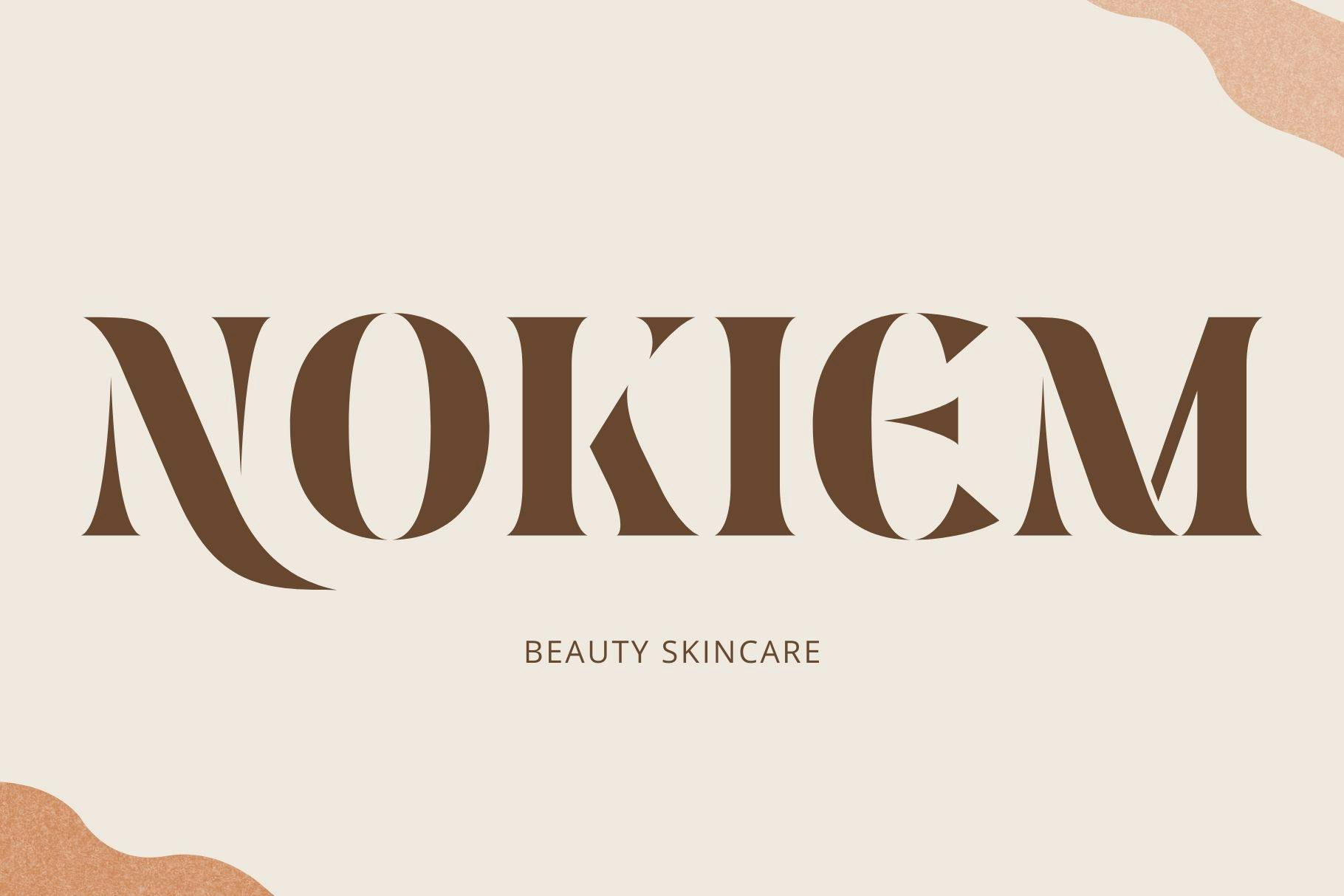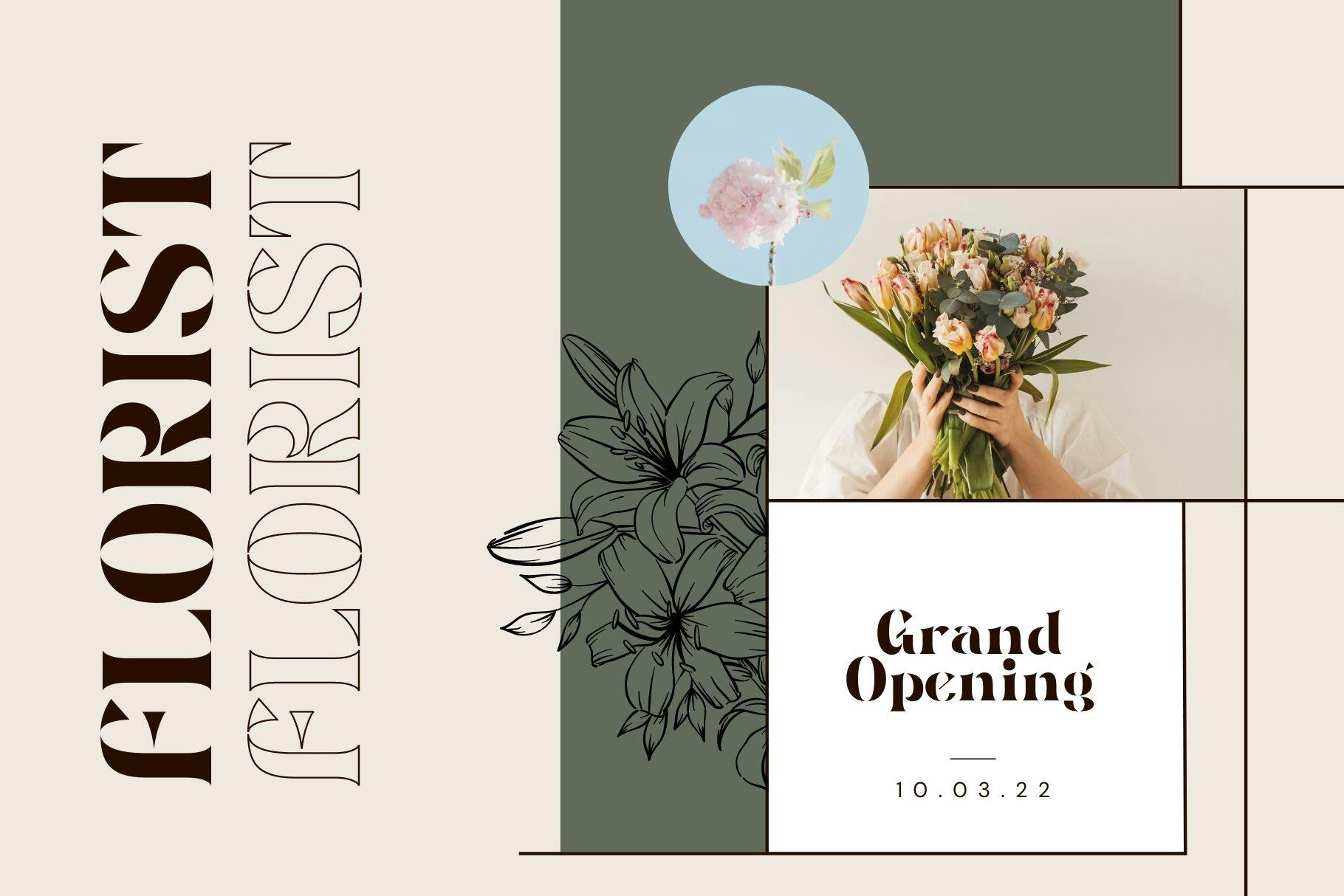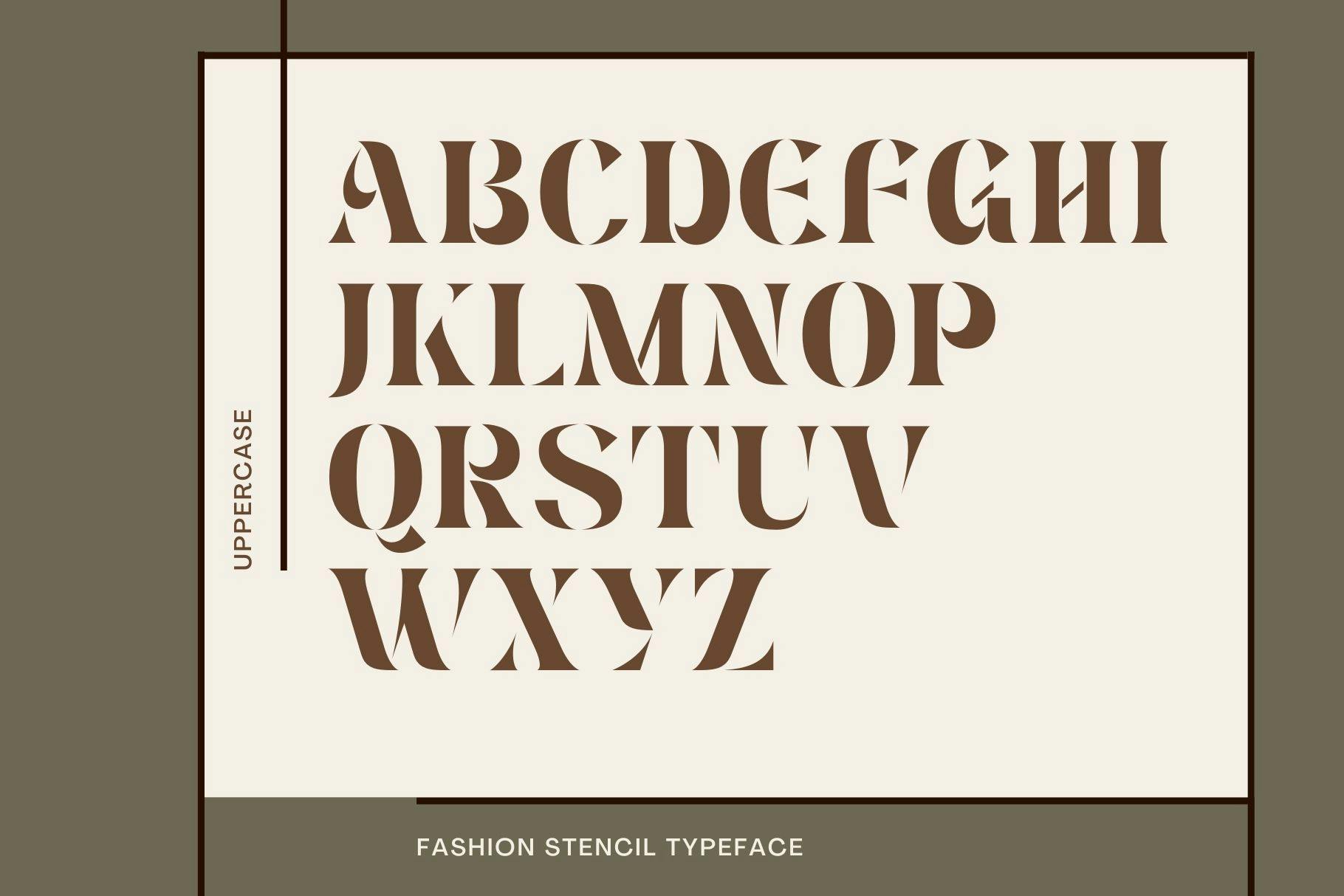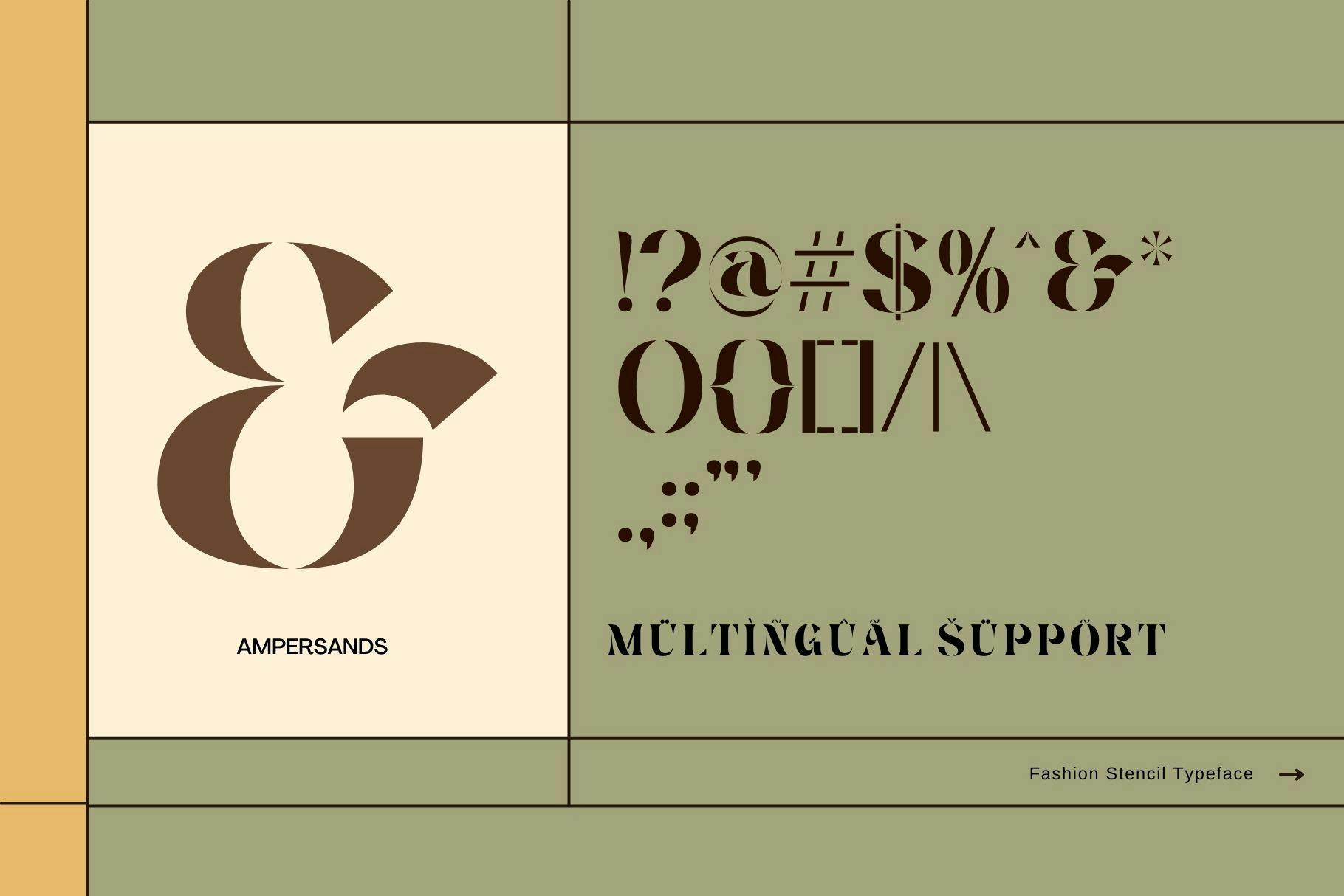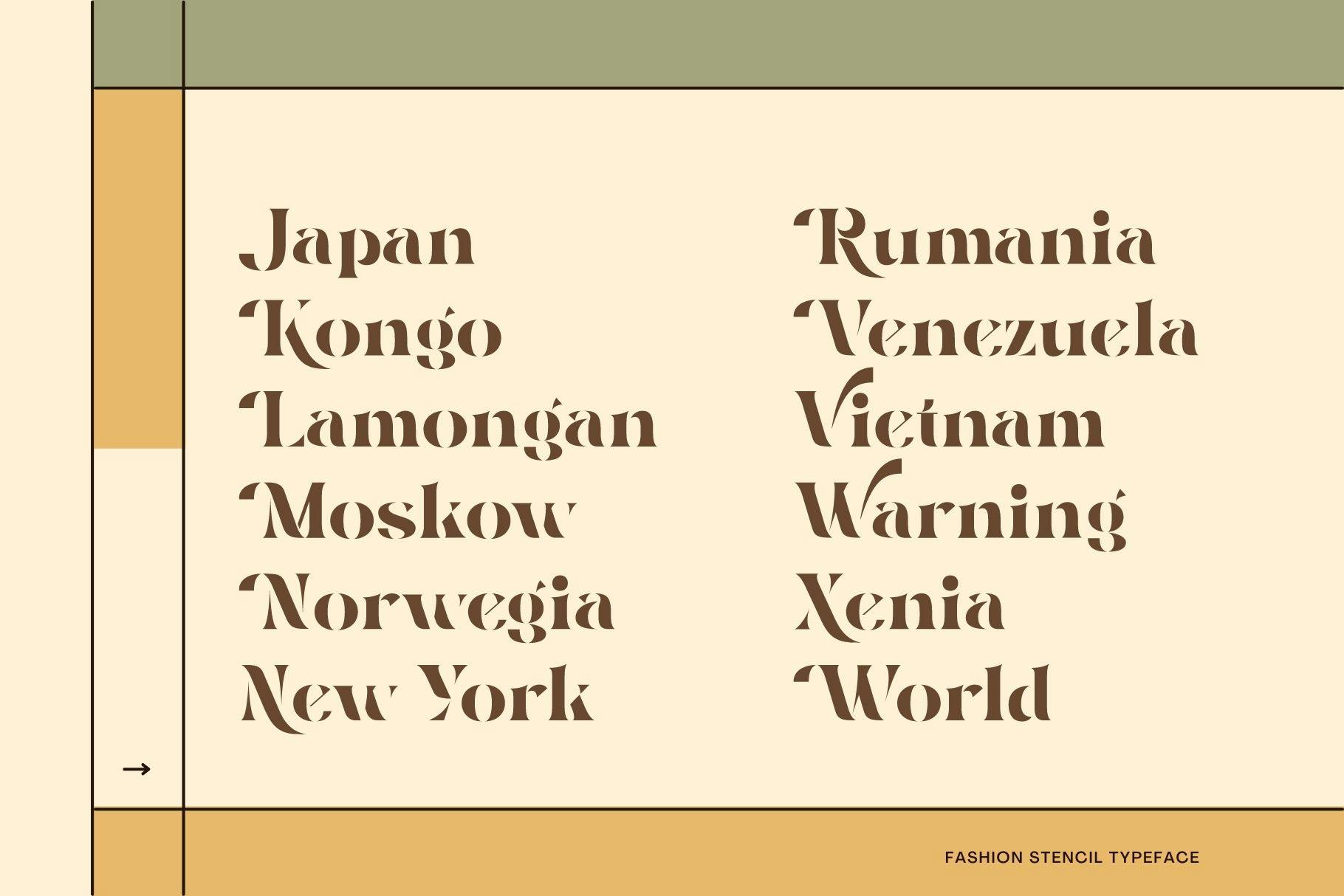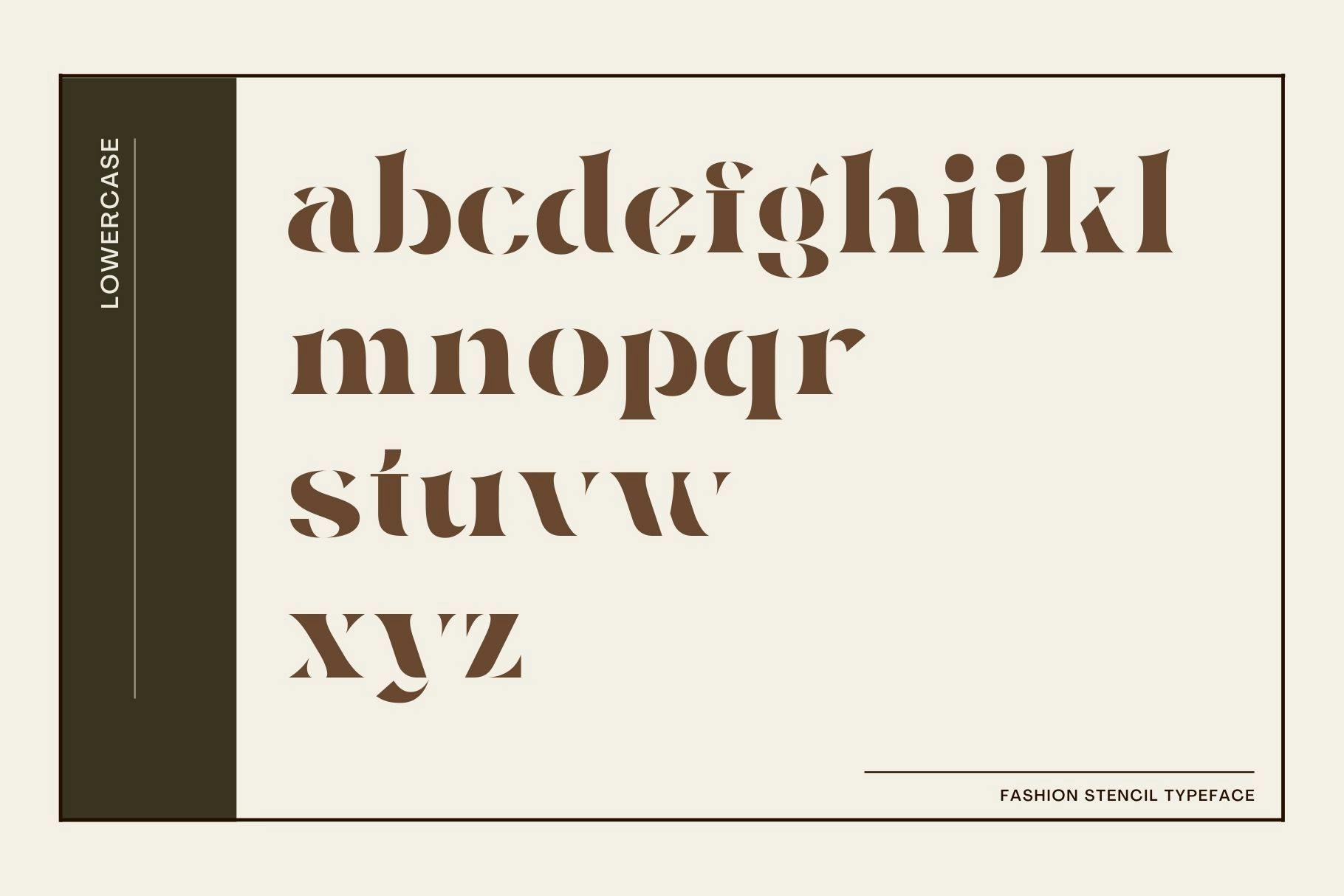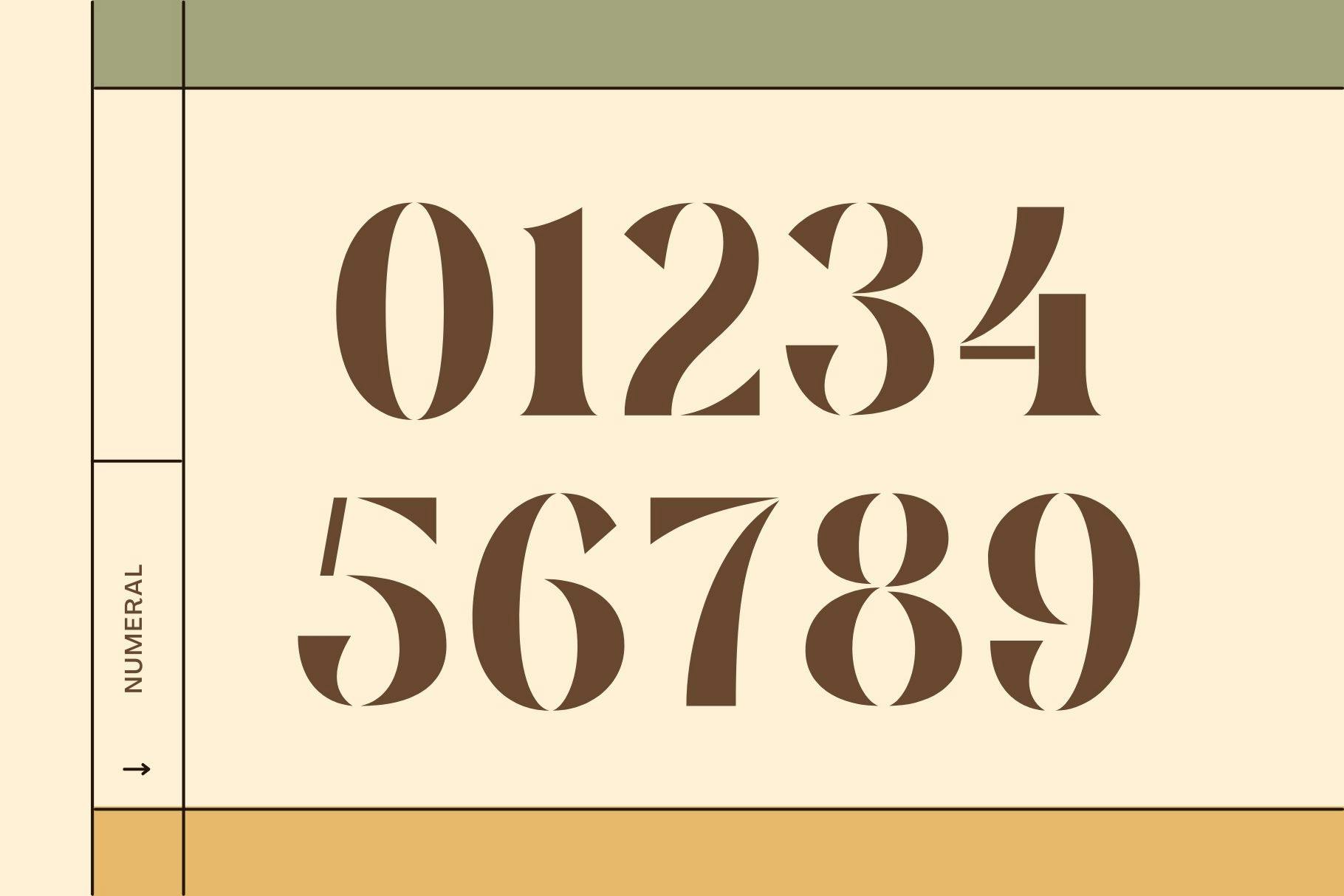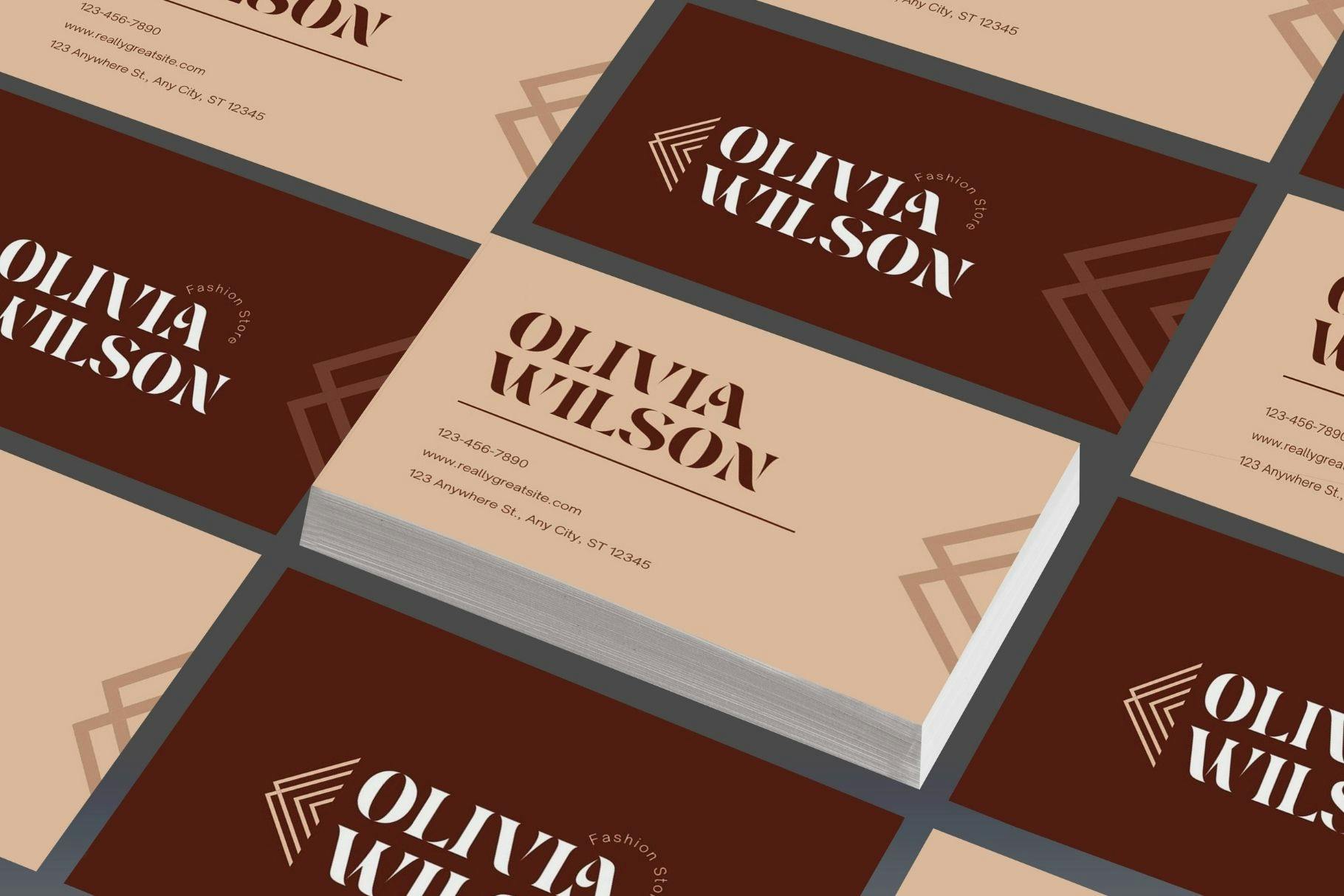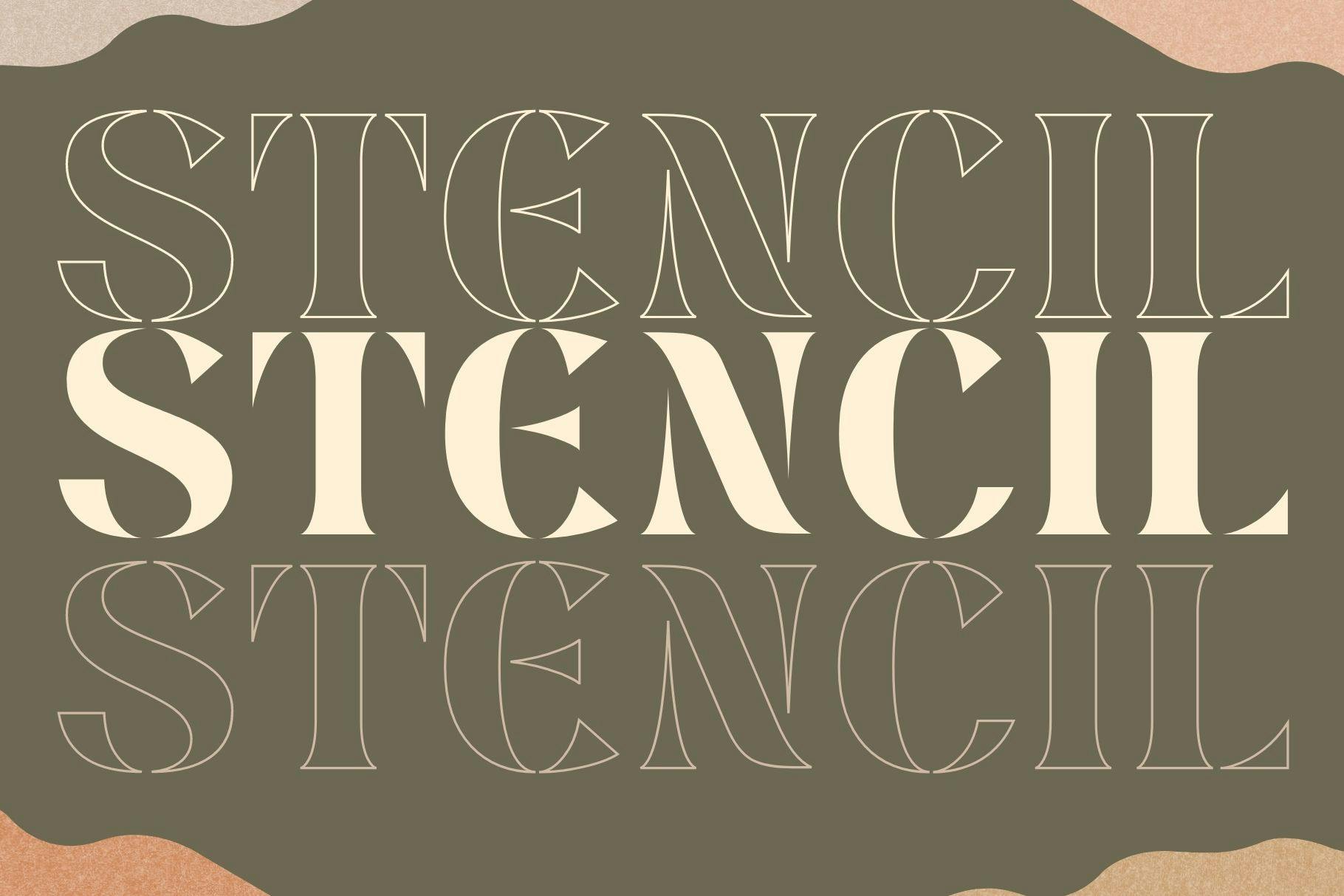
Fashion Stencil Logo Font
این فونت زیبا و مدرن، مناسب برای طراحی لوگو و پروژه‌های مختلف است.
فونت استنسیل فشن، هم‌عصر فونت‌های سریف،
فونت استنسیل فشن هارمونی تایپوگرافی زیبایی را برای تنوعی از پروژه‌های طراحی، از جمله لوگو و برندینگ، پست‌های شبکه‌های اجتماعی، تبلیغات و طراحی محصولات ارائه می‌دهد.